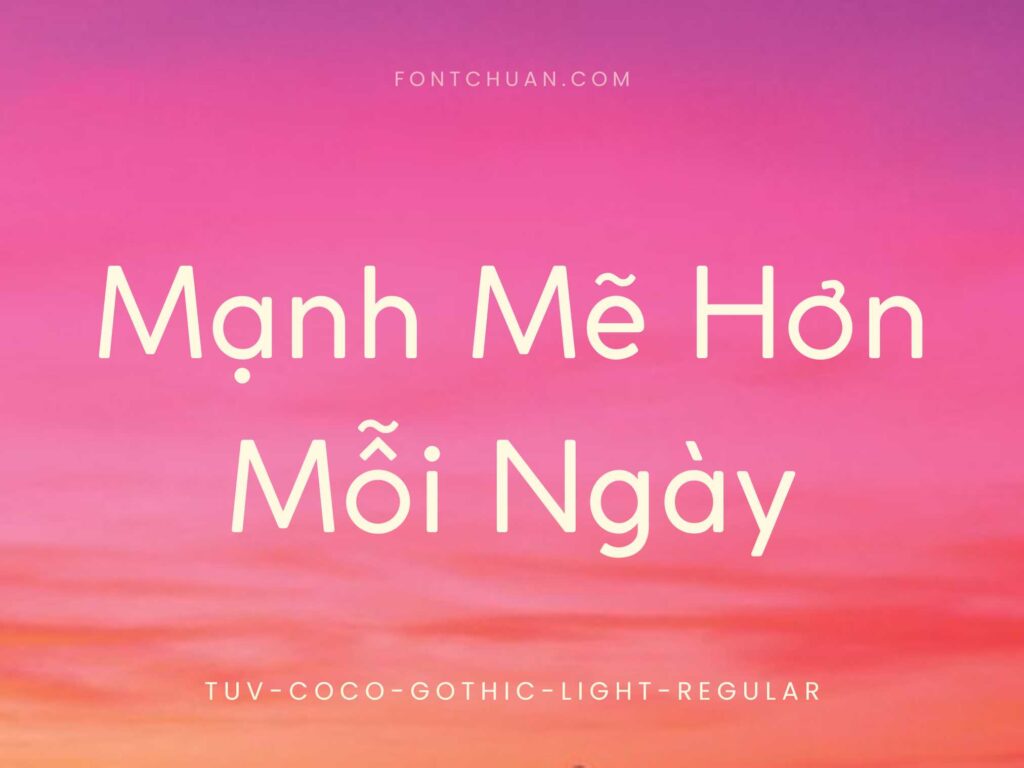
Font TUV Coco Gothic Light Và Regular Việt Hóa
Coco Gothic là một font chữ sans-serif hiện đại, được thiết kế bởi Cosimo Lorenzo Pancini và phát hành bởi Zetafonts. Font này lấy cảm hứng từ phong cách hình học retro của các kiểu chữ sans-serif đầu thế kỷ XX như Futura và Avantgarde, nhưng được làm mềm mại và hiện đại hơn nhờ các góc bo tròn nhẹ và thiết kế tối giản. Tên của bộ font được đặt theo biệt danh của biểu tượng thời trang Coco Chanel. Font đã được Việt hóa để hỗ trợ tiếng Việt bởi Thùy Uyên, giúp người dùng Việt Nam dễ dàng áp dụng trong các dự án thiết kế. Font này được sưu tầm và chia sẻ bởi thành viên của Font Chuẩn, đáp ứng nhu cầu sử dụng đa dạng trong cộng đồng thiết kế.
Đặc điểm thiết kế của Coco Gothic bao gồm các hình dạng hình học mềm mại và tối giản, tạo cảm giác hiện đại và tinh tế. Font này phù hợp cho các ứng dụng như thiết kế logo, tiêu đề, bố cục tạp chí và các dự án sáng tạo khác. Các ngành nghề phù hợp bao gồm công nghệ, quảng cáo và giáo dục.